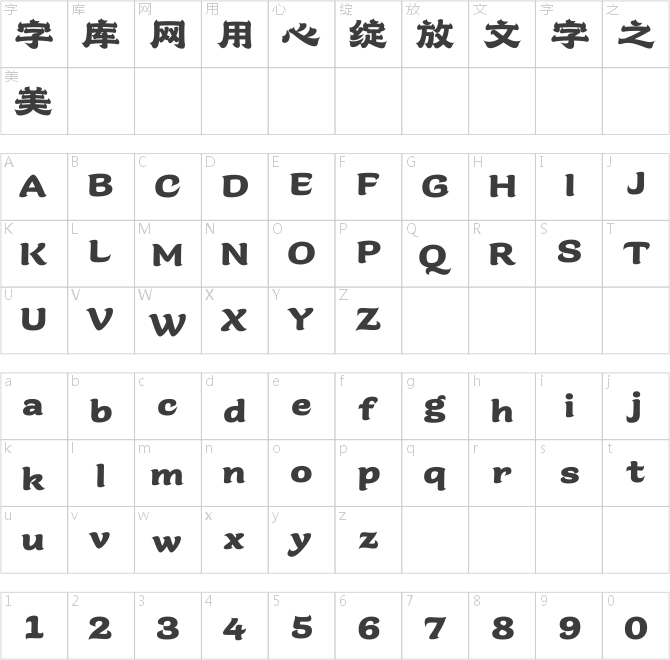
字体名称: 汉仪赤云隶
汉仪赤云隶
汉仪赤云隶是由知名设计师行行珂与汉仪字库合作打造的一款带有隶书韵味的设计字体。这款字体运用现代设计语言,在隶书的基础上改造创新,给予了传统字体新的生命力。
汉仪赤云隶曾入选Award360°年度设计100、《第十四届亚太设计年鉴》、《Design360°n.84#特刊#》和《字赋不凡2》。